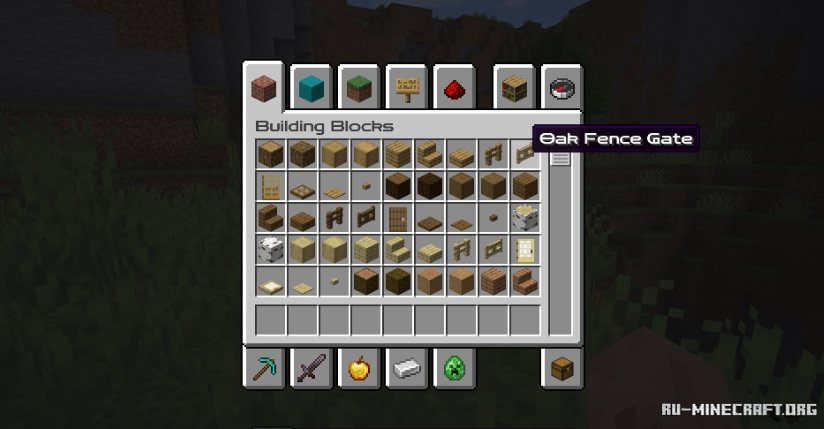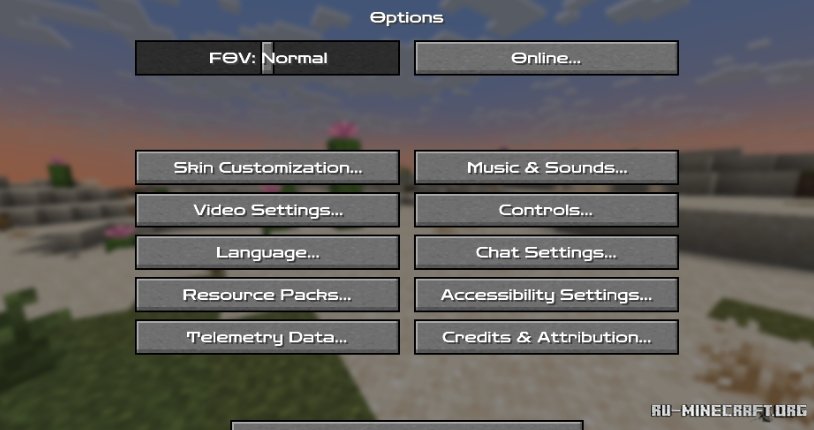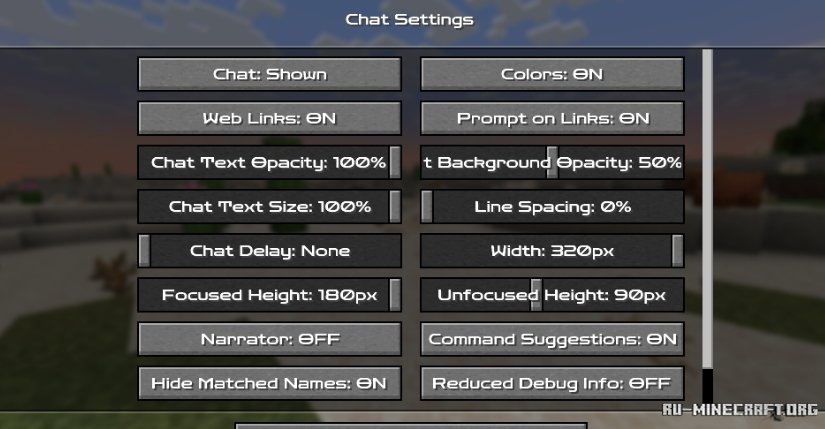
Представляем вашему вниманию замечательный пакет Zen RPG Font, благодаря которому вы сможете изменить привычный шрифт на некий стиль без засечек, он неплохо впишется в атмосферу вашего майнкрафта. Замечательный пакет, который позволит вам изменить данный аспект, и открыть замечательный шрифт в собственной игре.